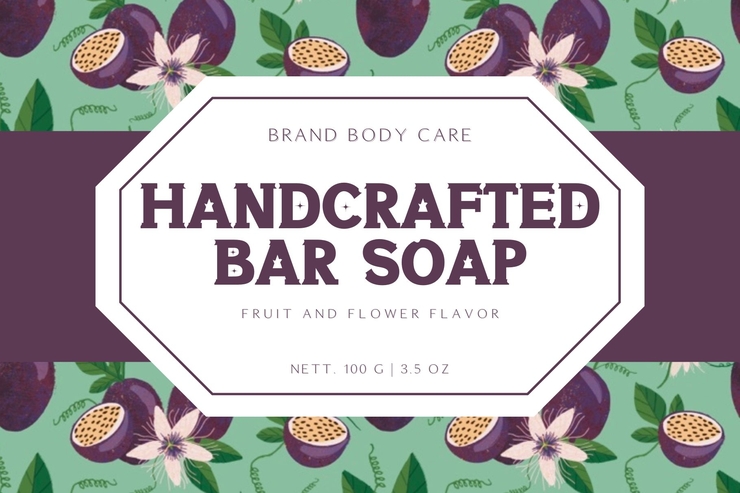
Cybera Modern Tech-Stil Elegante dekorative englische Schrift
Cybera ist eine futuristisch-technisch inspirierte dekorative englische Schrift mit schlanken, scharfen Strichen und futuristischen geometrischen Details. Sie zeichnet sich durch eine moderne Cyber-Ästhetik mit klaren Linien und ausgewogenen Glyphenstrukturen aus, die Hightech-Mode mit elegantem visuellem Temperament verbindet. Diese stilvolle Schrift eignet sich perfekt für Tech-Markenlogos, Gaming-Visuals, digitale Poster, Webbanner, Sci-Fi-Themenverpackungen und Social-Media-Grafikdesign. Komplett mit Groß- und Kleinbuchstaben ist sie hochgradig skalierbar und lässt sich leicht an Farben, Größen und Layouts anpassen, ohne ihre futuristische Tech-Textur zu verlieren. Geeignet für Grafikdesigner, Tech-Studios und kommerzielle Branding-Projekte, um auffällige moderne visuelle works.Free für den kommerziellen Gebrauch zu schaffen / Kein Copyright1